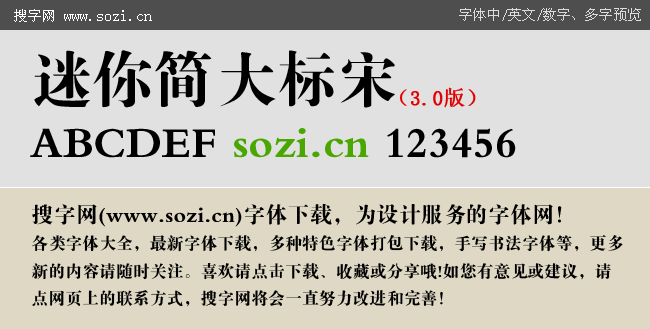
迷你簡(jiǎn)大標(biāo)宋
搜字網(wǎng)提供一款迷你簡(jiǎn)大標(biāo)宋中文字體下載。迷你簡(jiǎn)大標(biāo)宋是一款嚴(yán)謹(jǐn)?shù)淖煮w,筆畫(huà)粗細(xì)分明,布局嚴(yán)謹(jǐn)且沉穩(wěn),常被用作各類(lèi)書(shū)籍、報(bào)紙、雜志等標(biāo)題字。